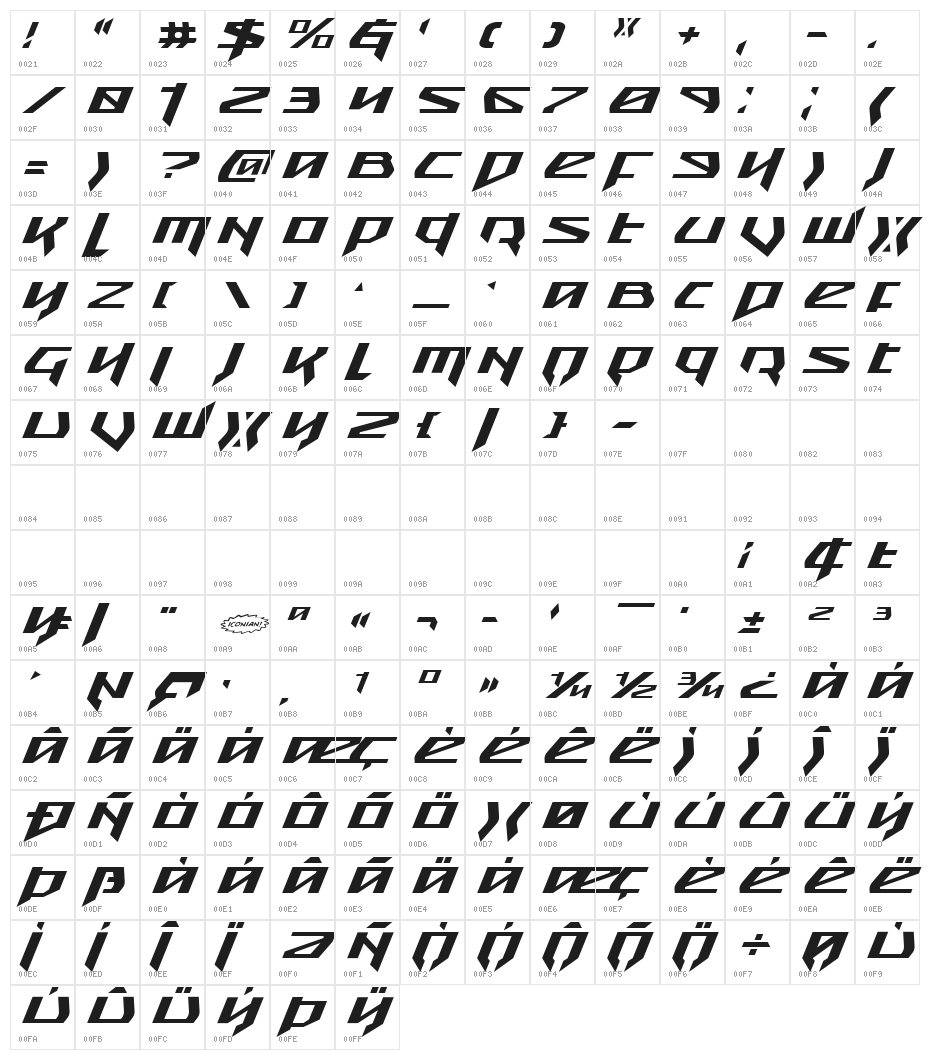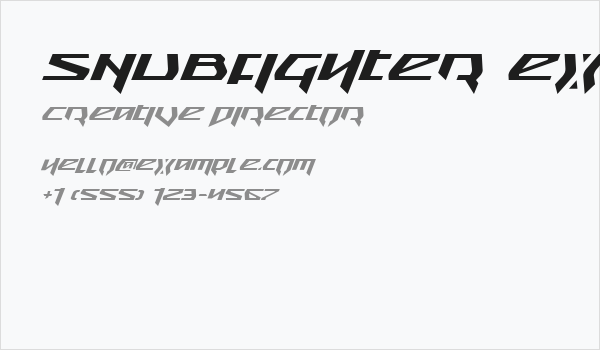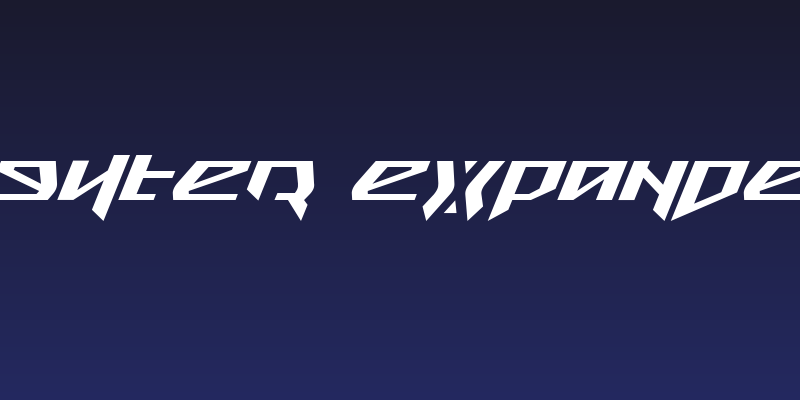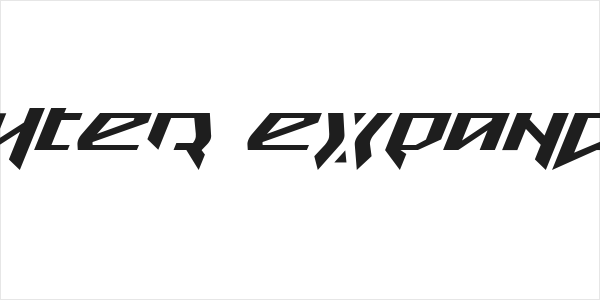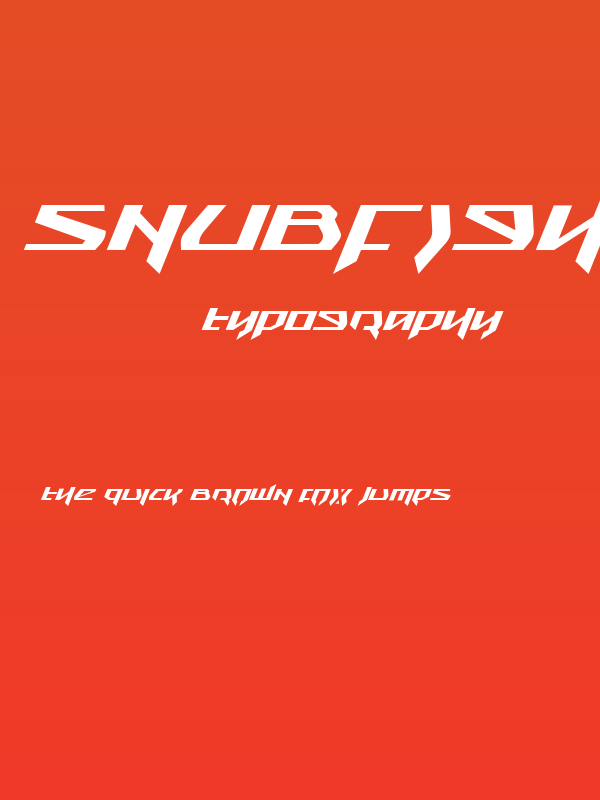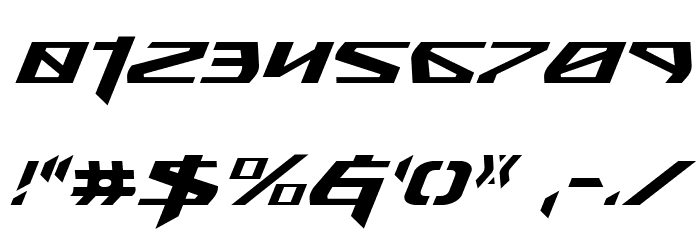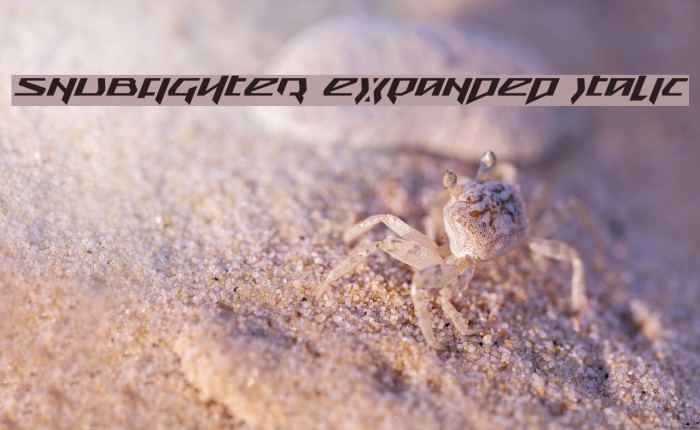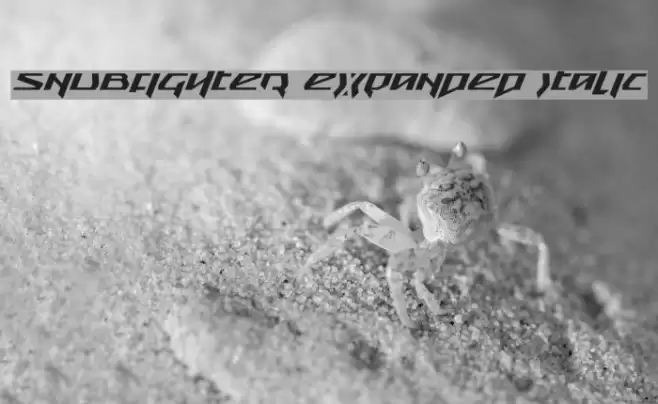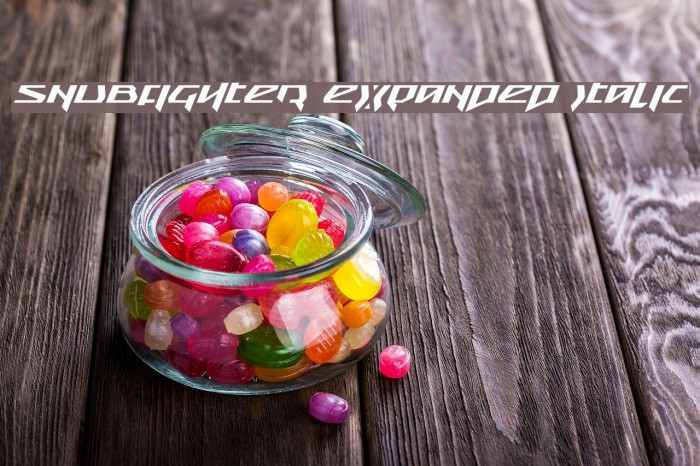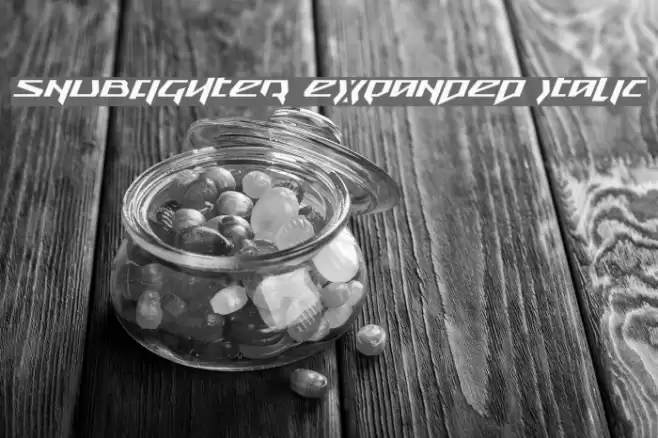
Snubfighter Expanded Italic Font
| Categorias | Sci-fi |
| Largura | Expanded |
| Estilo geral | Futuristic |
| Projetos propostos | Ideal for sci-fi themed designs, video game titles, movie posters, and branding that requires a modern and edgy look. |